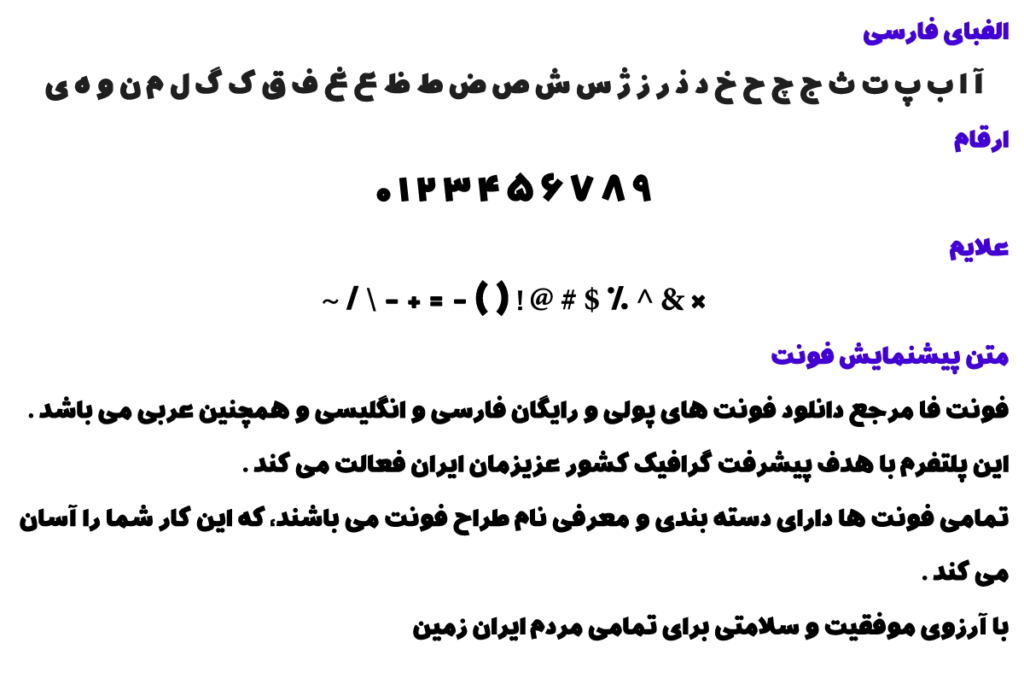
فونت فارسی سپهبد – Sepahbod
طراح فونت: سعید پوناکی نوع فونت: فونت تایپوگرافی و فونت عنوان
توضیحات و معرفی فونت سپهبد
فونت فارسی سپهبد ( Sepahbod ) از مجموعه فونت های آزاد و برتر می باشد، همچنین نوع فونت تایپوگرافی و عنوان می باشد.
فونت فوق العاده زیبای معرفی شده توسط سعید پوناکی در سال 1400 طراحی و ساخته شده است.
این تایپ فیس به یاد شهید سردار سلیمانی طراحی و منتشر شده است.
همچنین این فونت در یک وزن پر رنگ است.
در لیست زیر می توانید وزن این فونت فوق العاده زیبا را ببینید.
- Sepahbod Bold